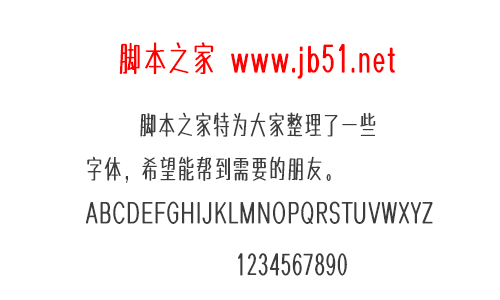
楊任東超棒體是一款工整、規(guī)范的藝術(shù)字體,橫平豎直,線條勻稱(chēng),結(jié)體大方,特色鮮明,適合應(yīng)用于藝術(shù)設(shè)計(jì)、平面宣傳設(shè)計(jì)、網(wǎng)頁(yè)設(shè)計(jì),書(shū)法字帖等領(lǐng)域,歡迎喜歡此字體的朋友前來(lái)下載使用。